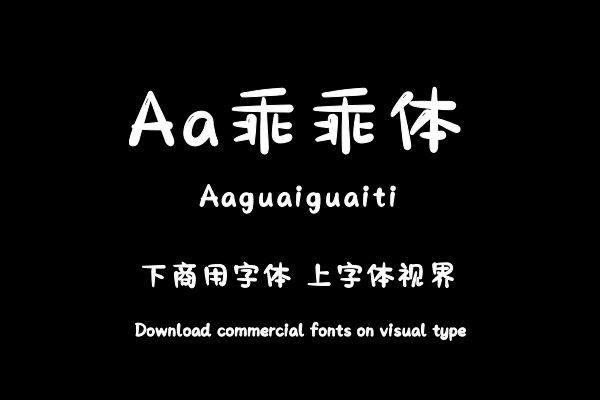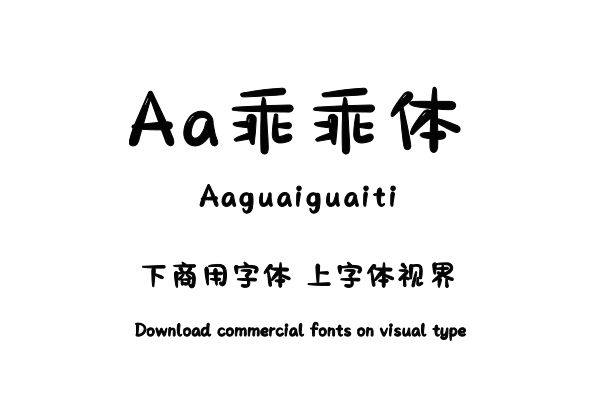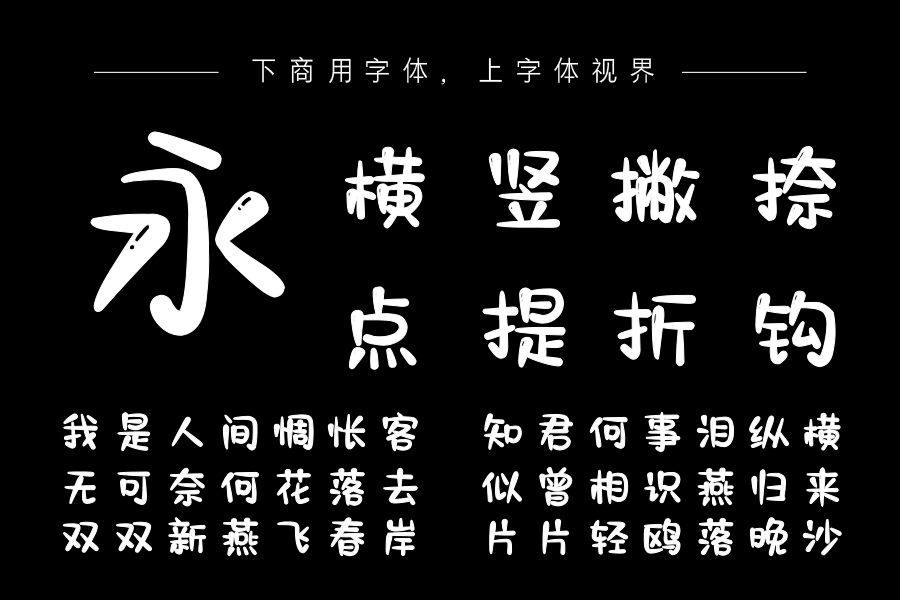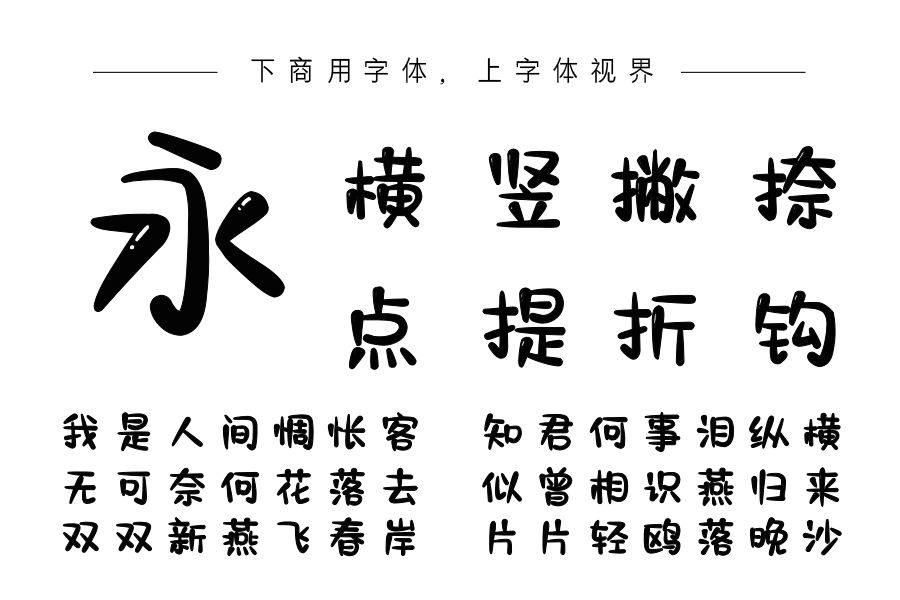
Aa乖乖体整体圆润可爱,部分笔画设计如水滴状饱满,字形丰满立体,字体自带高光装饰更显灵动俏皮,充满童趣。非常适合儿童、母婴、绘本、动画等设计场景中使用。购买须知:“下载服务费”与“字体VIP”所获得字体 仅用于个人非商用, 商用请联系付费授权。本字体为电脑用字,手机没有root权限不支持直接手机换字(手机如何root,请自行百度搜索教程)。购买前请先 了解清楚后再付款 ,字体为虚拟产品无法回收 一旦购买不支持退款。